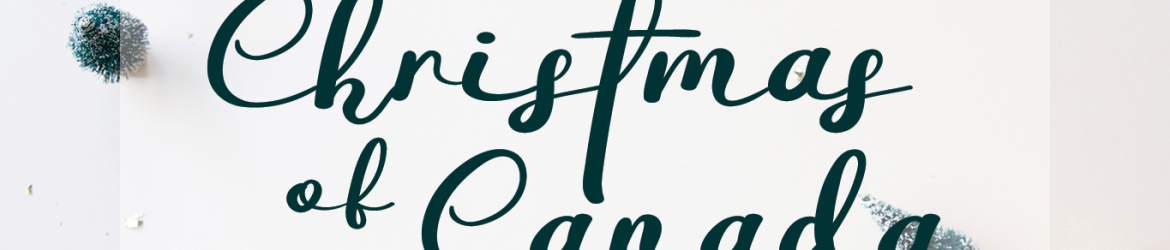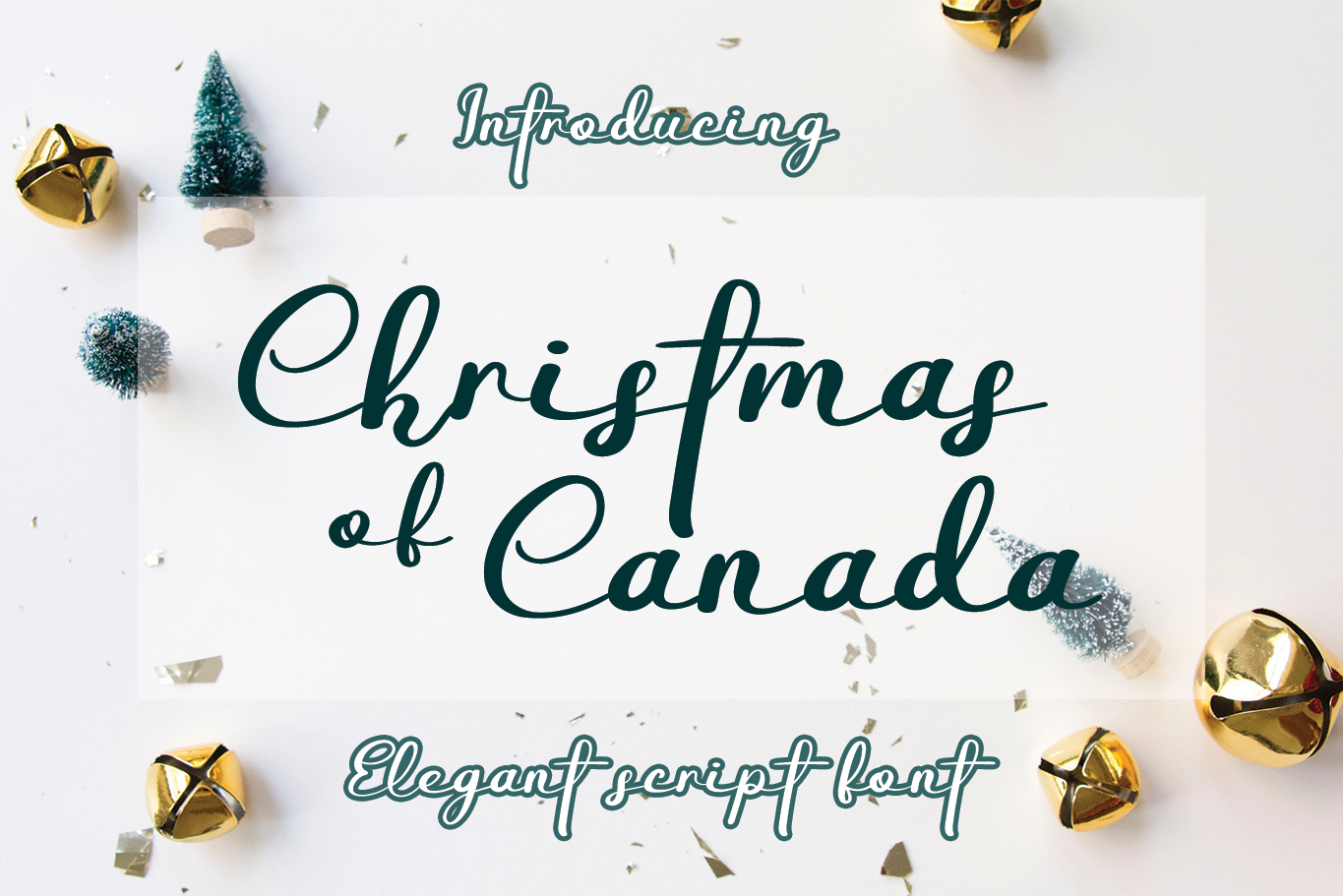
Christmas Of Canada Font
Esta é uma fonte script que apresenta caracteres encantadores e divertidos, com uma aparência alegre e dançante ao seguir a linha do baixeixo. Os personagens desta fonte têm um toque de vida e entusiasmo que certamente destacarão seus textos mais criativos. Seja para cartas personalizadas, gráficos ilustrativos ou qualquer projeto que requer uma pitada de encanto na escrita, essa fonte é perfeita. As sugestões do designer Erik Studio garantem que este seja o elemento especial que tornará seu trabalho ainda mais memorável e atraente.